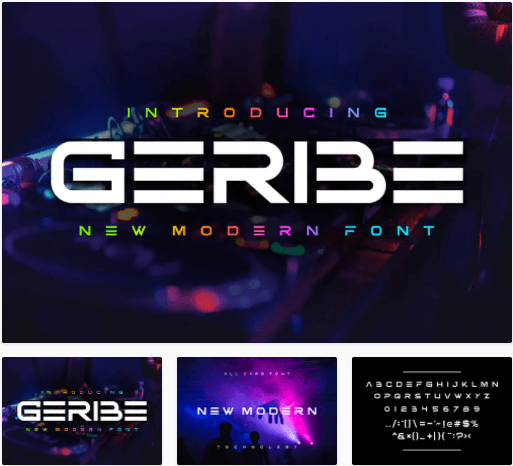
Geribe Font
Представляем наш новый продукт Geribe Font - Modern Font
Geribe Font - Modern Font - это смелый и аутентичный дисплейный шрифт. Шрифт подходит для любого брендового проекта, такого как логотип, печать на футболках, киберспорт и многое другое. выдающийся в широком диапазоне контекстов.